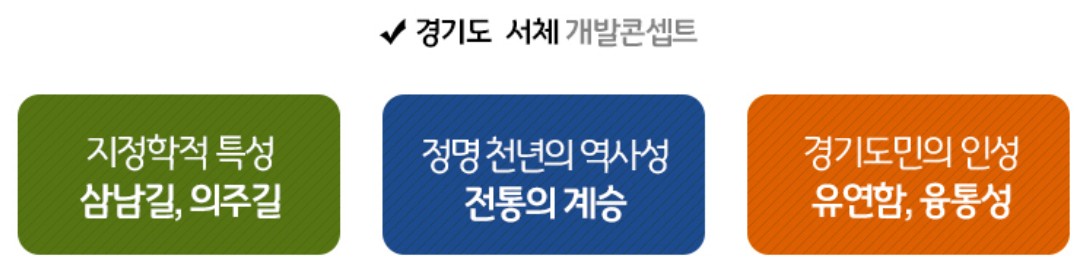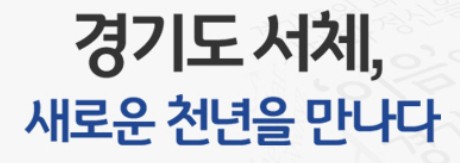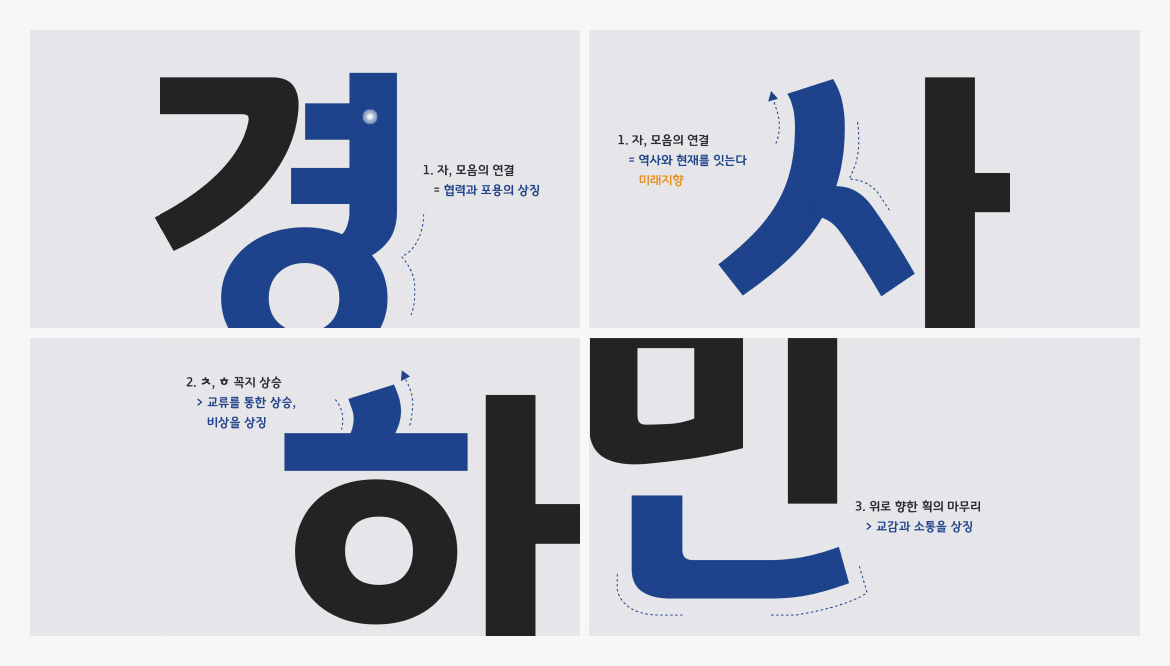
경기도서체는 경기도의 역사, 문화, 지정학적 특성을 반영하여 제작된 무료 폰트입니다. 경기 정명이후 천년을 이어온 전통과 한반도의 중심적 위치를 고려하여 '이음'이라는 콘셉트로 디자인되었습니다. 경기천년제목과 경기천년바탕 두 가지 스타일로 제공되며, 누구나 자유롭게 사용할 수 있습니다.
경기도서체 폰트의 특징
경기도서체는 한글의 유연한 연결성을 강조하며, 부드러운 곡선과 세련된 직선이 조화를 이루는 디자인이 특징입니다. 경기천년제목은 강한 가독성과 현대적인 미감을, 경기천년바탕은 전통적인 서체와 실용성을 강조합니다. 이 폰트는 영상, 인쇄, 웹 디자인 등 다양한 환경에서 활용될 수 있습니다.